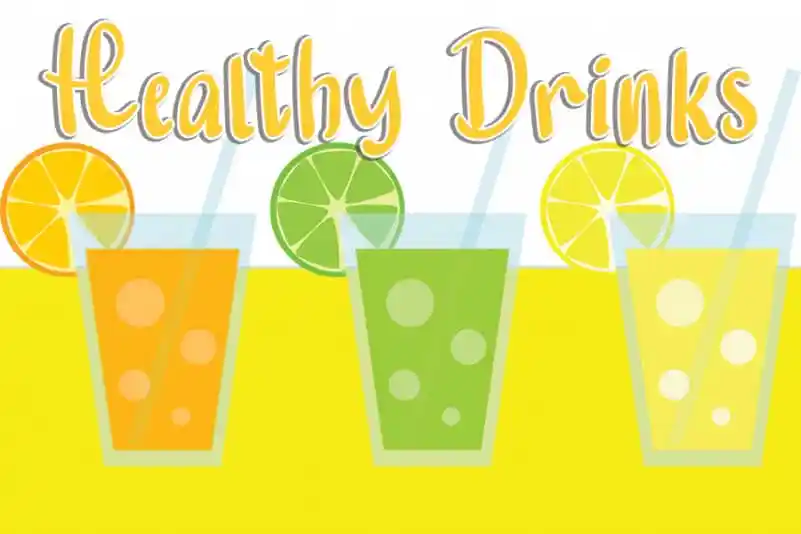
Healthy Drinks Display Font é uma fonte tipográfica romântica e doce que traz caracteres dançando ao longo da linha-base. Suas formas delicadas e alegres estão perfeitamente adaptadas para escrever convites de casamento, cartões de felicitações ou qualquer design que possa precisar de um toque personalizado e romântico. Esta fonte é ideal para aqueles designers que procuram uma maneira divertida e criativa de incorporar elementos delicados e alegres em seus projetos, especialmente quando querem transmitir um forte sentimentos de amor e celebração. Inspirada na arte da calligrafia, ela traz uma graça única à qualquer projeto onde você deseje expressar seu lado mais romântico.